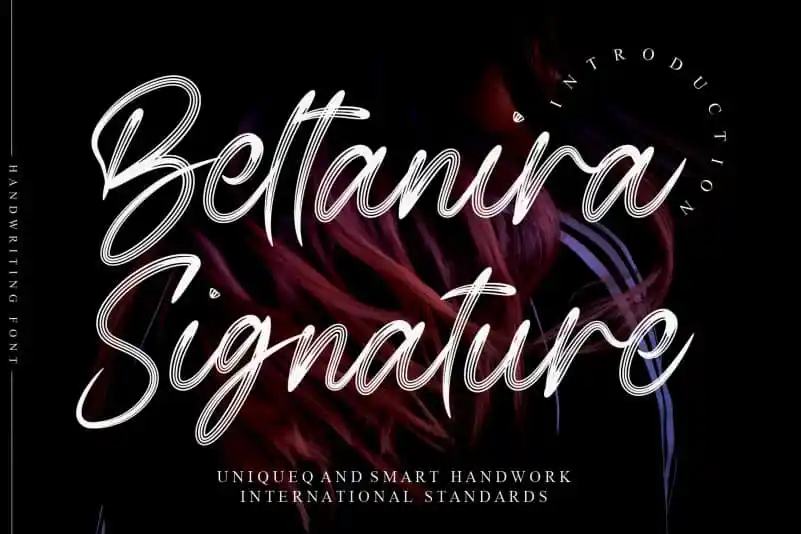
Beltanira Signature Script Font – Download Grátis
Descubra a magia do Beltanira Signature Script Font, uma deliciosa criação para seus projetos visuais únicos. Desenvolvida para os amantes da arte tipográfica e criativos sem limites, esta fonte Brush é perfeita para aqueles que buscam um toque de romance no design. Ideal para anúncios, logotipos personalizados ou qualquer projeto onde uma escrita delicada traga vida a sua obra, essa fonte consegue capturar o olhar e fazer você se apaixonar pela criatividade intrínseca em cada letra. Seu formato elegante permite que você personalize o texto, permitindo que você atinja seus objetivos de design com liberdade. Com a Beltanira Signature Script Font, transforme qualquer projeto no qual ela seja usada em algo inovador e único. Experimente agora e faça sua arte florescer através da escrita elegante desta fonte.